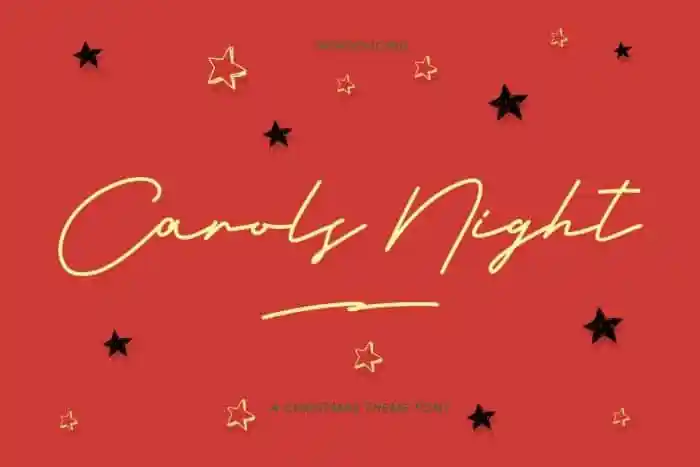
Carols Night Handwritten Font – Download Grátis
A Carols Night Handwritten Font é uma elegante tipografia script monoline criada para retratar a autêntica escrita a mão. Esta fonte traz a sensação de escrever-se diretamente, não apenas um design cuidadosamente elaborado. Ela se assemelha perfeitamente ao estilo natural da escrita, sendo uma escolha ideal para projetos como marca, logotipos, moda, cosméticos, roupas, diários pessoais e livros de lookbook, cards de agradecimento, apresentações elaboradas e ambientes glamorosos. Carols Night é perfeita tanto para trabalhos comerciais quanto para criações mais artísticas, oferecendo um toque autêntico e único ao seu projeto.